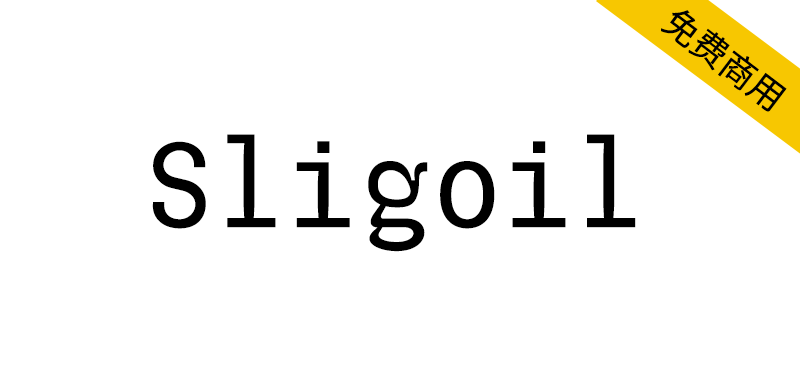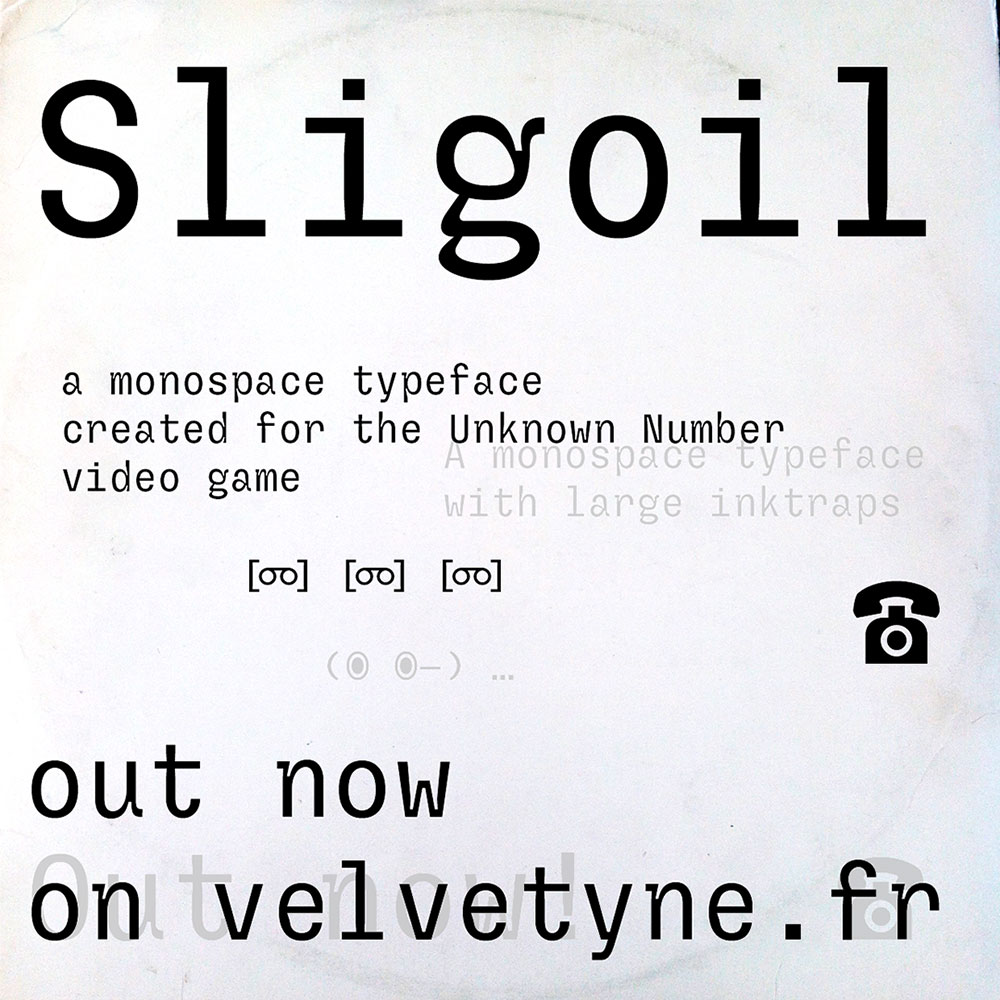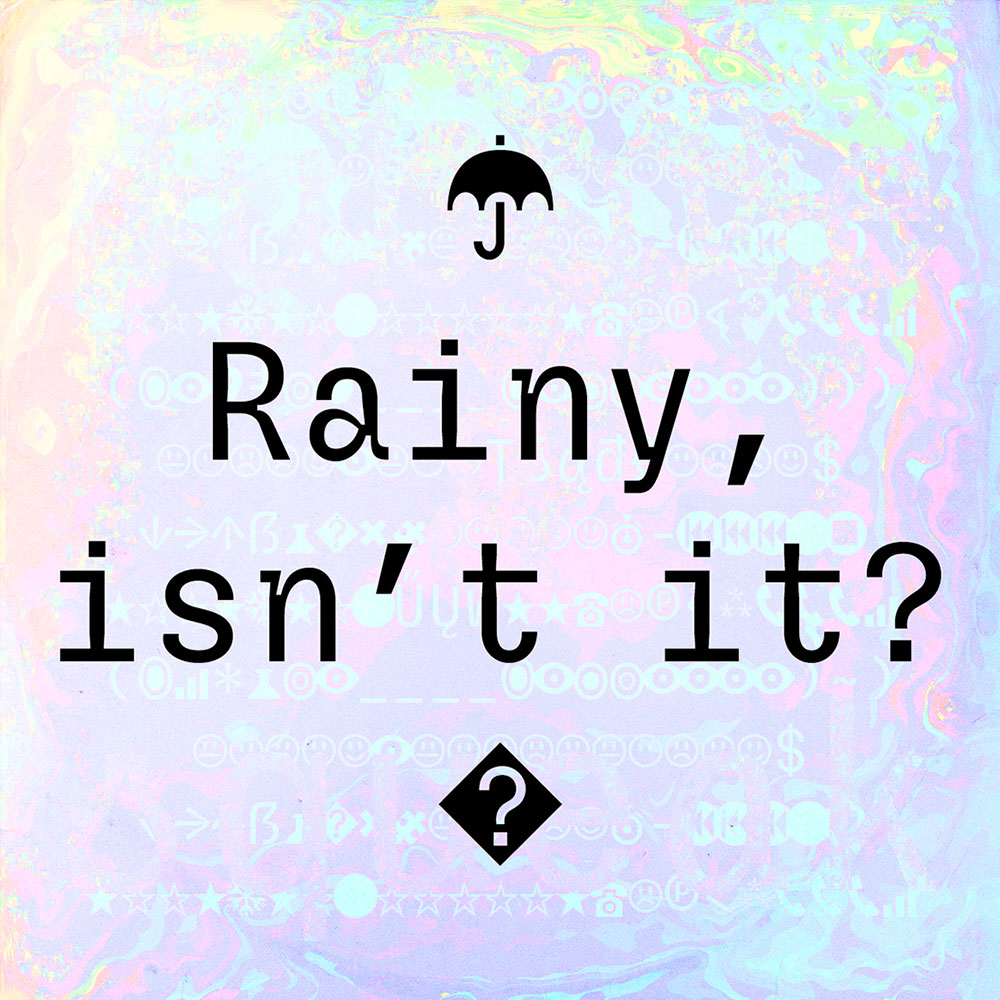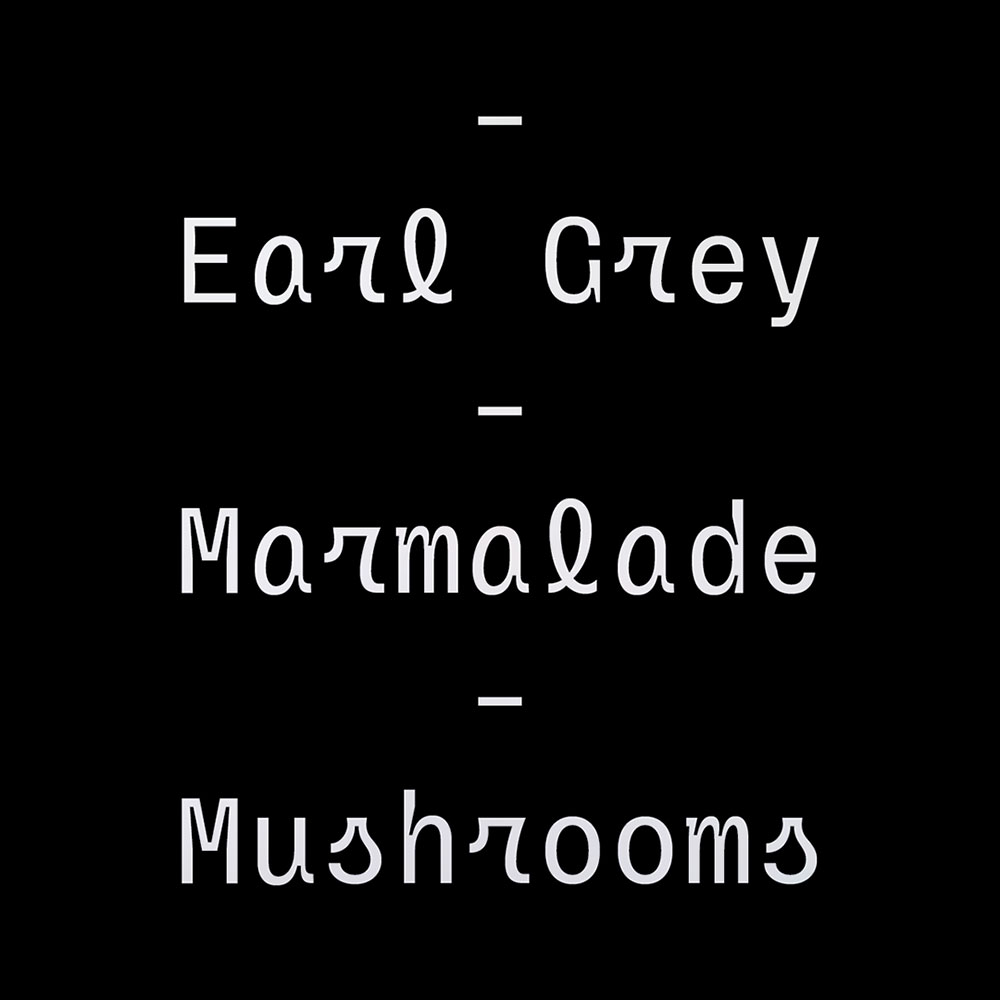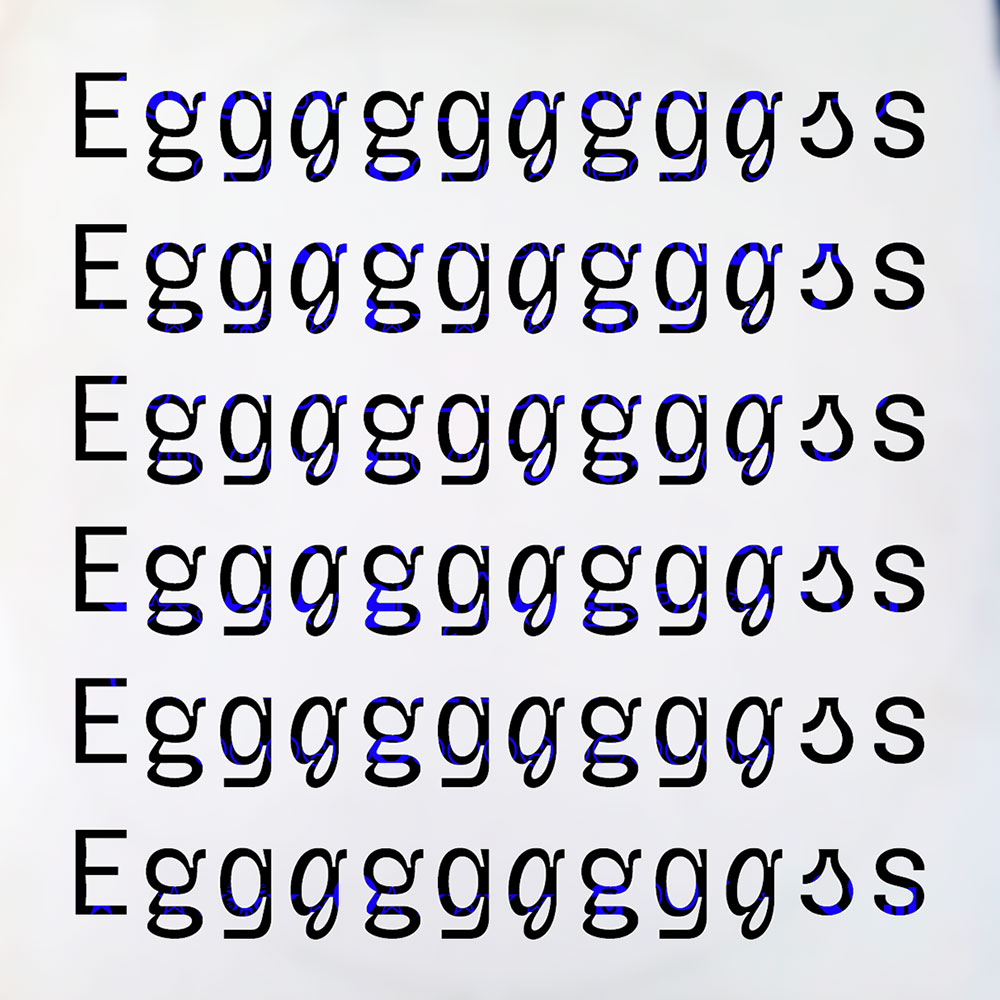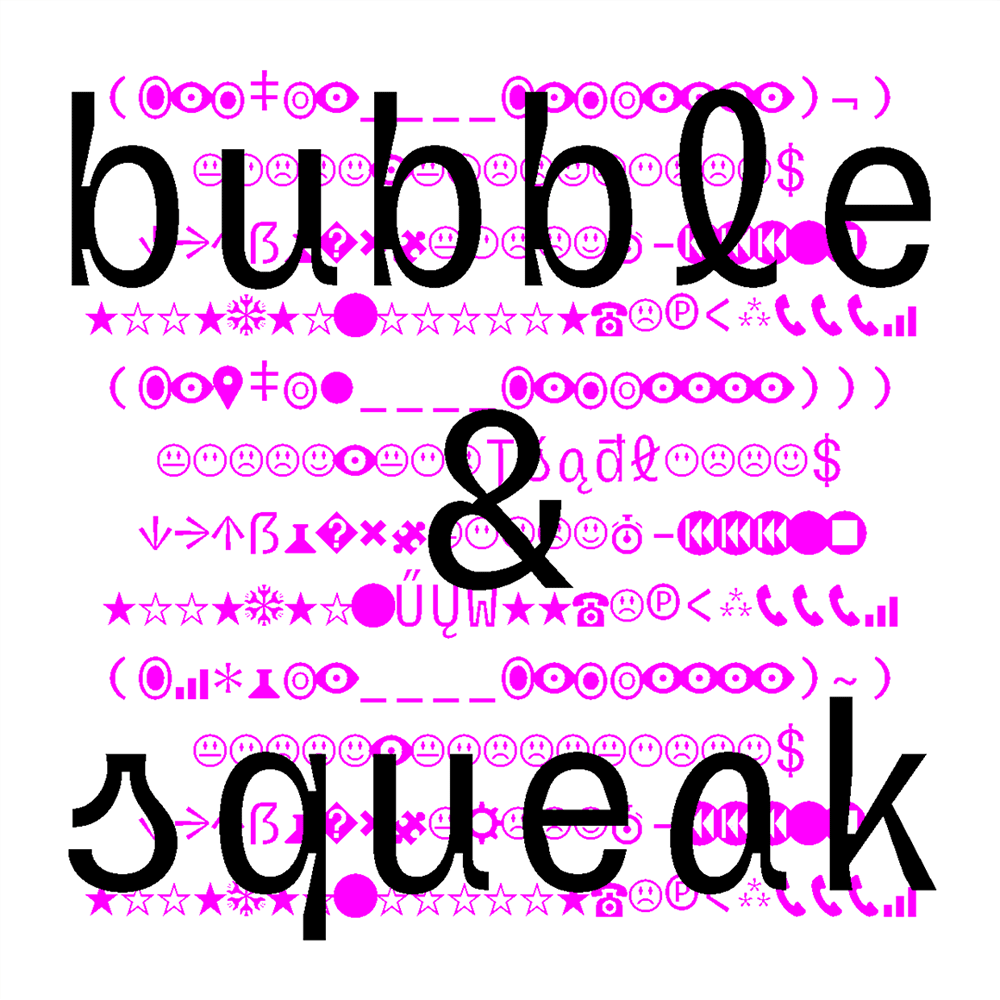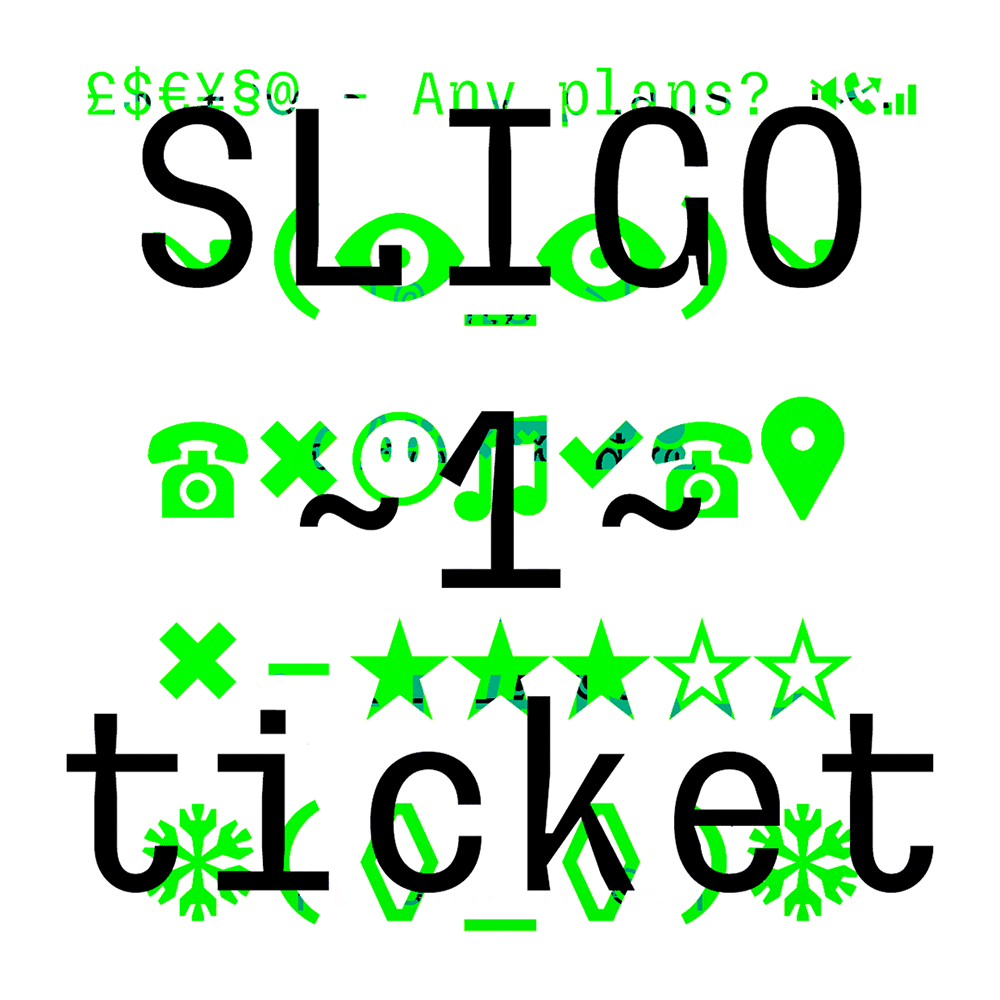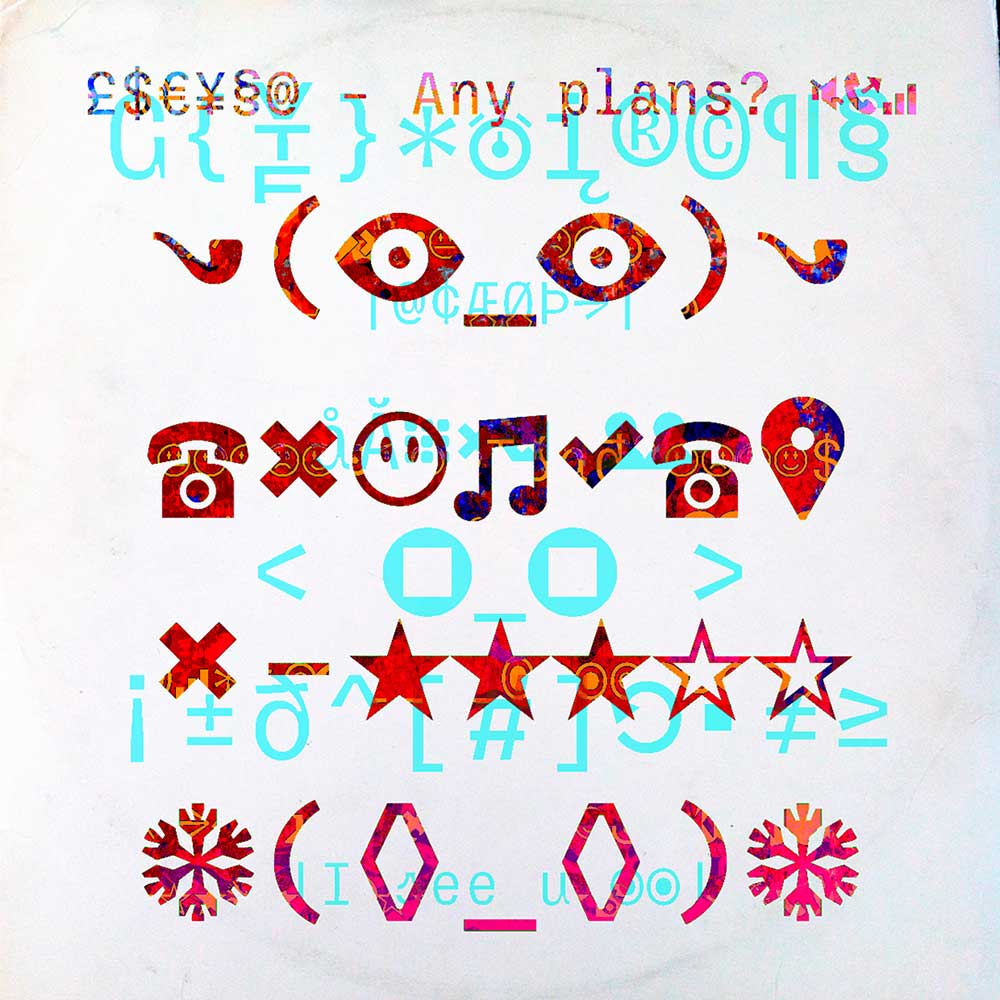
Sligloil是一种等宽字体。它是为Godolphin Games发行的《Unknown Number》游戏的界面而设计的。“Sligloil”也是游戏中一个邪恶虚构公司的名字。
Sligloil字体受到了不列颠群岛文化的影响(当然是马修·卡特的作品,但也有爱尔兰威士忌酿酒厂的标志),也受到了老式太空学员键盘上的字母的影响(由麻省理工学院生产)。它为基于拉丁语的欧洲语言提供了广泛的语言支持,并提供了一系列符号和替代形式(包括直立斜体字母)。
Sligoil is a monospace typeface. It has been designed for the interface of the Unknown Number game, published by Godolphin Games. "Sligoil" is also the name of an evil fictional company within the game.
The Sligoil typeface has been influenced by the culture of the British isles (the work of Matthew Carter, of course, but also signs on Irish whiskey distilleries) and also by the letters on vintage Space Cadet keyboards (produced by the MIT). It presents wide language support for Latin-based European languages and a collection of symbols and alternate forms (including upright italic letters).